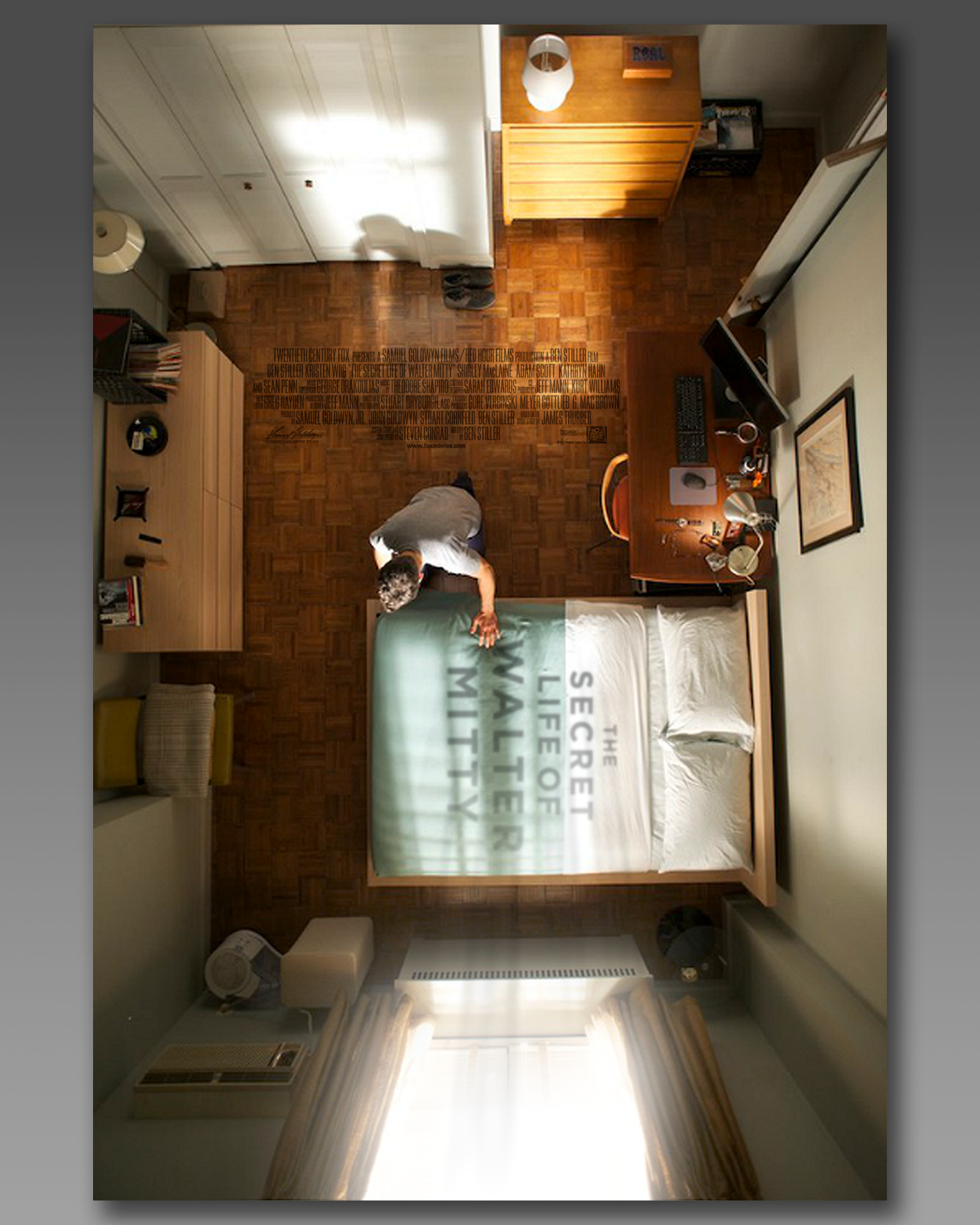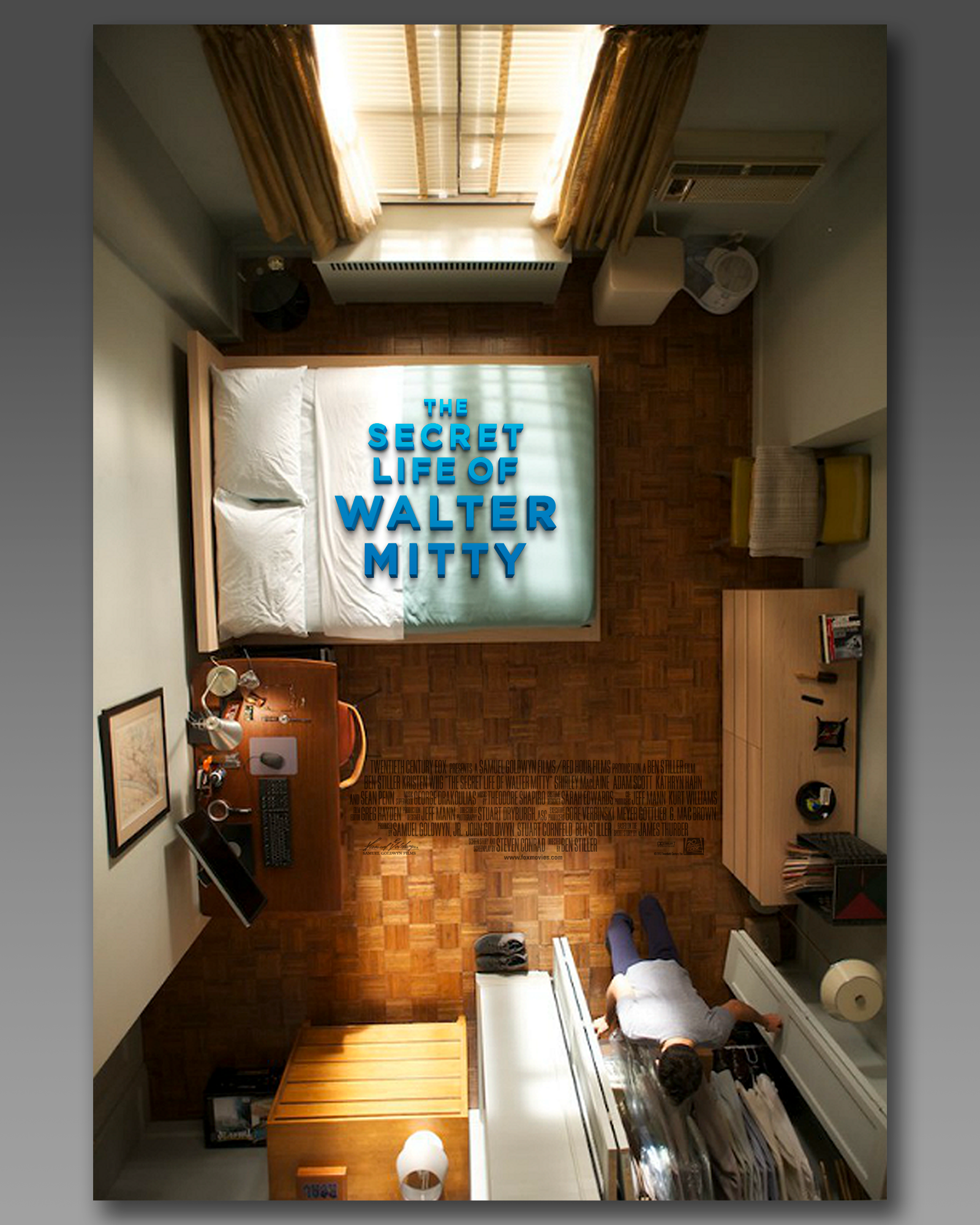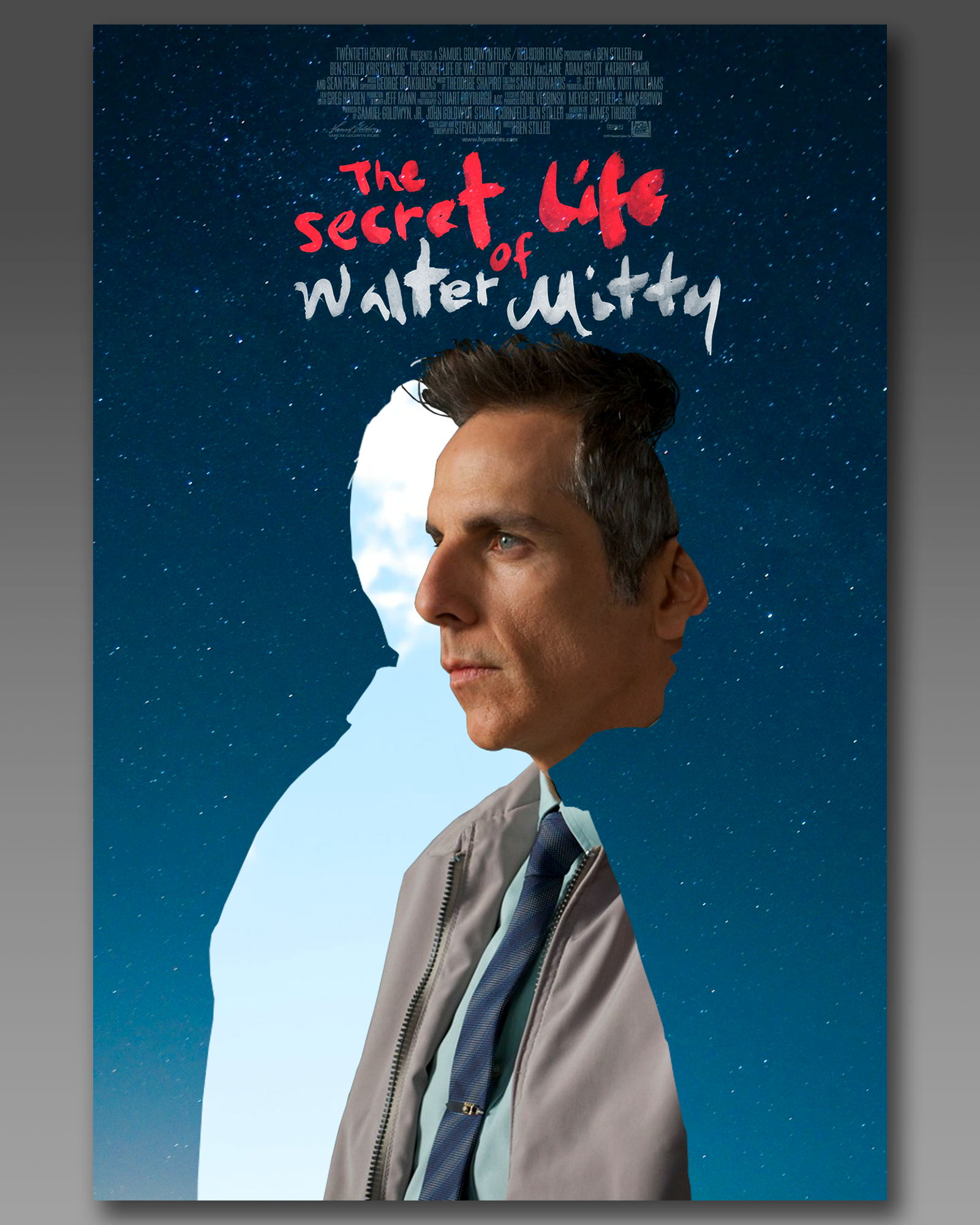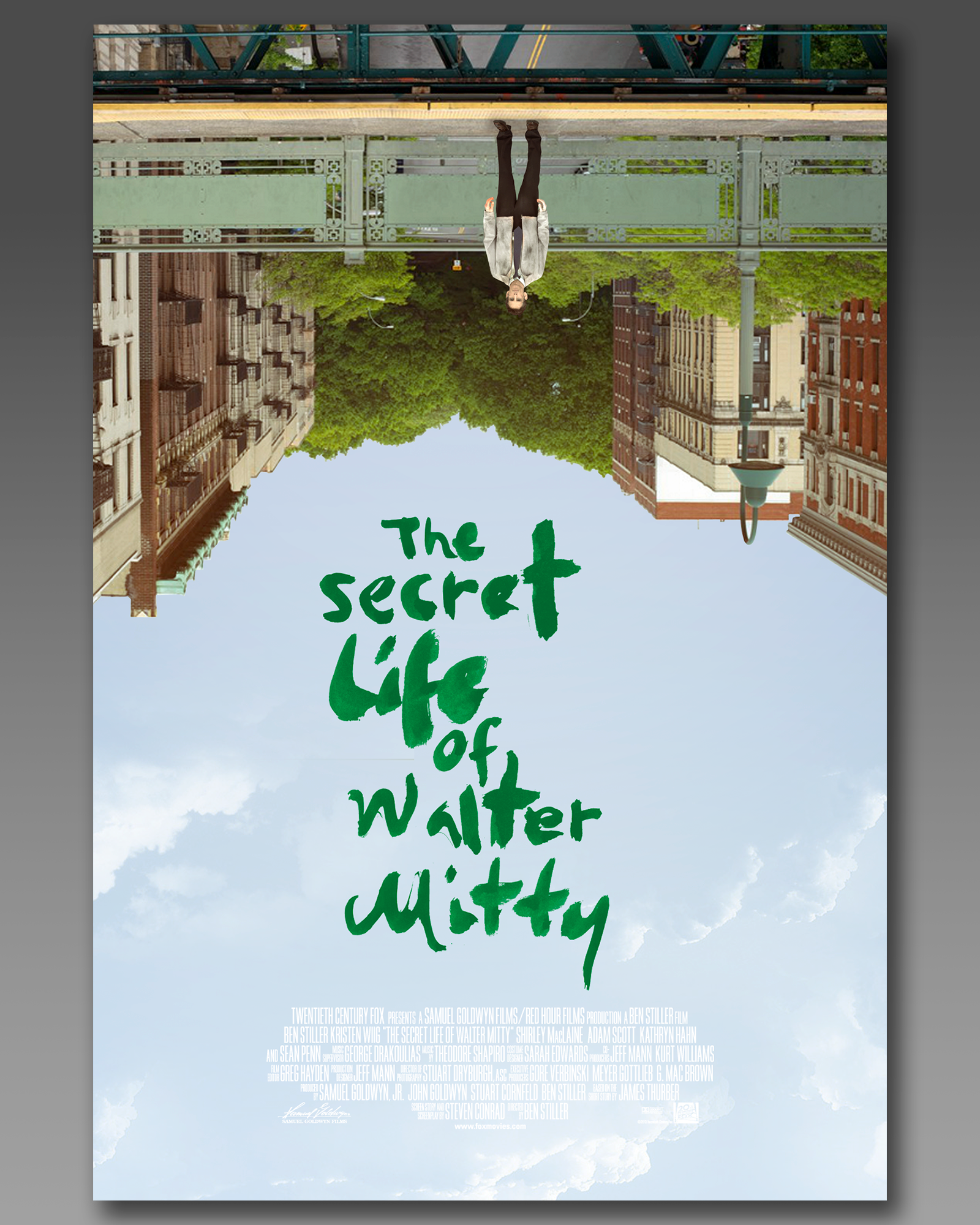
The Secret Life of Walter Mitty
Poster design exploration
Una pequeña selección de mi exploración de diseño de póster y tipografía para la maravillosa película La vida secreta de Walter Mitty. Experimentando con escenas surrealistas y la integración de la tipografía, explorando desde la caligrafía a mano hasta la tipografía 2D y 3D.